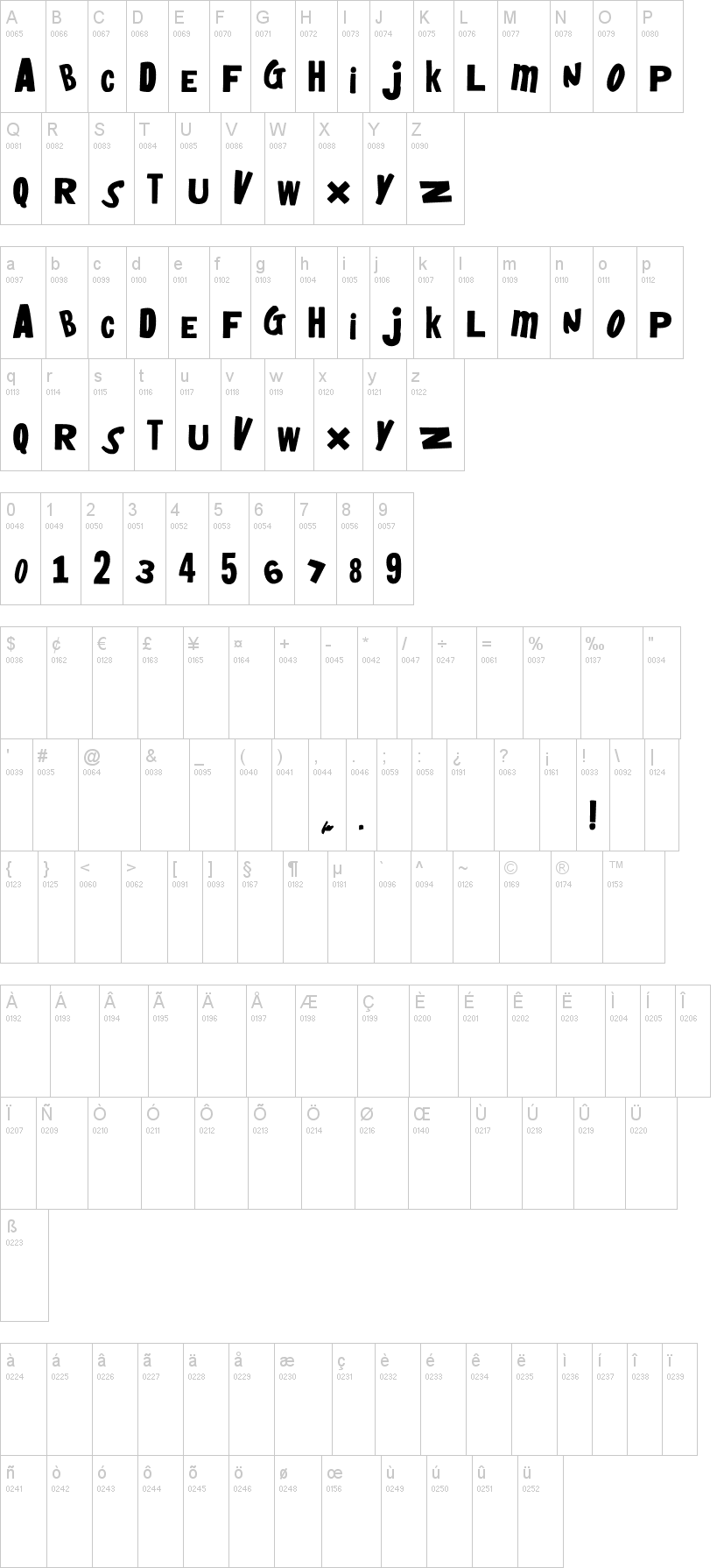
HeyBoy! HeyGirl! 是一种非常受欢迎的手写风格字体,它的风格清新、活泼、自然,适用于各种场合。这种字体的笔画粗细不均,字母之间的空隙也比较大,看起来非常自然和放松。HeyBoy! HeyGirl! 字体常用于卡片、海报、广告、包装设计以及装饰性文字设计等场合,使设计更加富有情感和个性化。内容介绍
HeyBoy! HeyGirl!是一款非常不错的手写艺术字体,具有很好的视觉感,适合于文化类的宣传设计、商业类品牌的广告和产品包装设计以及个性化文字排版等较多场景。